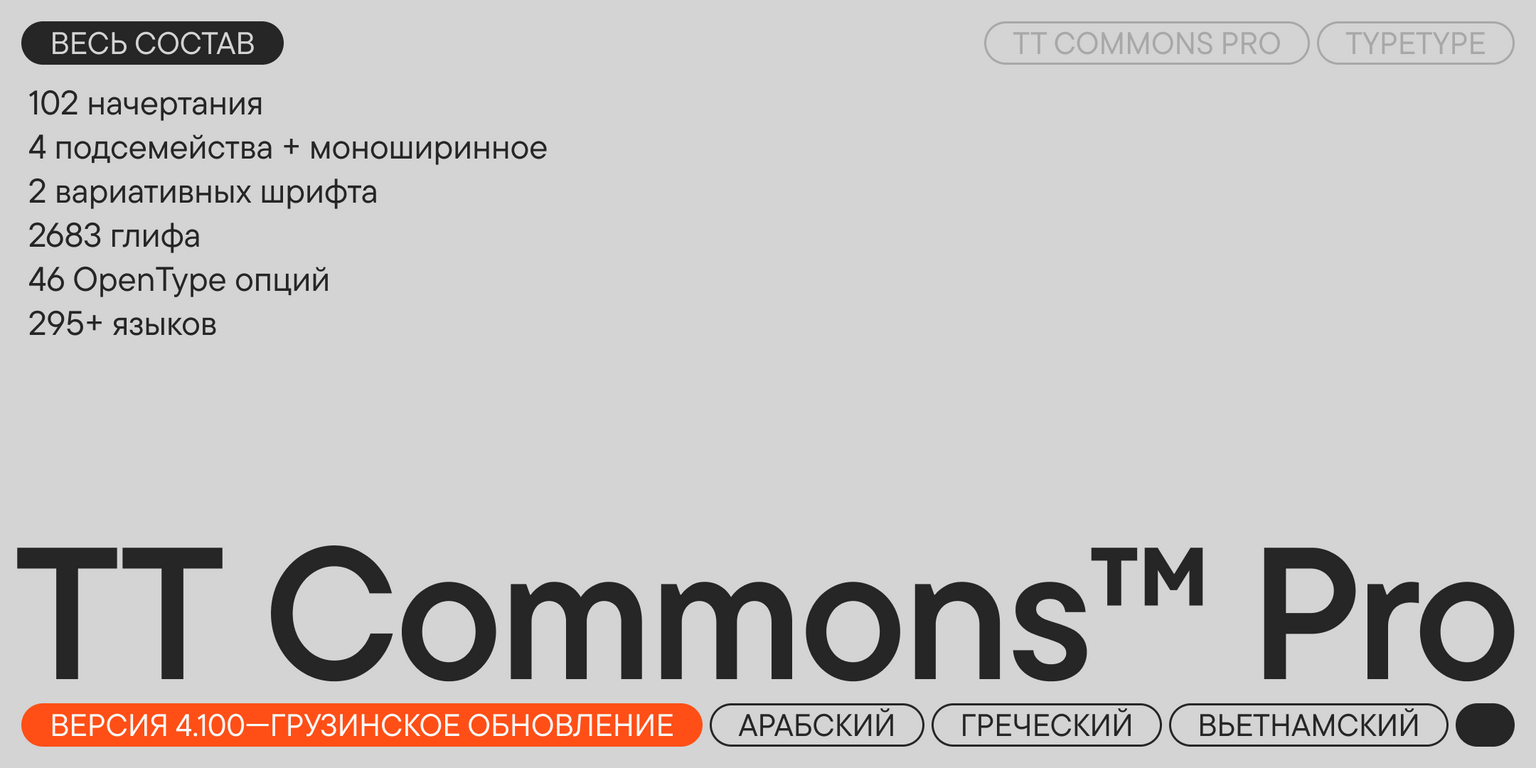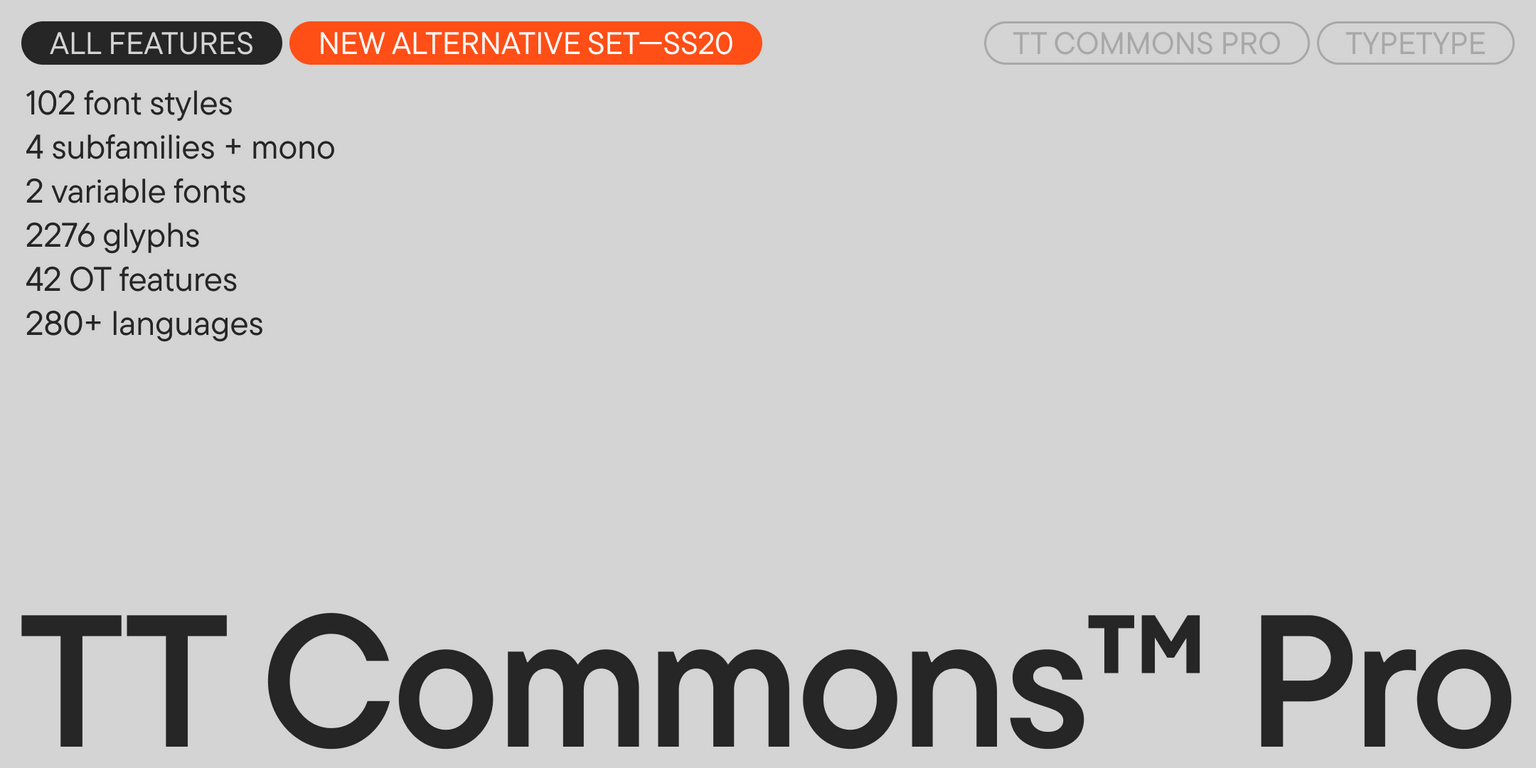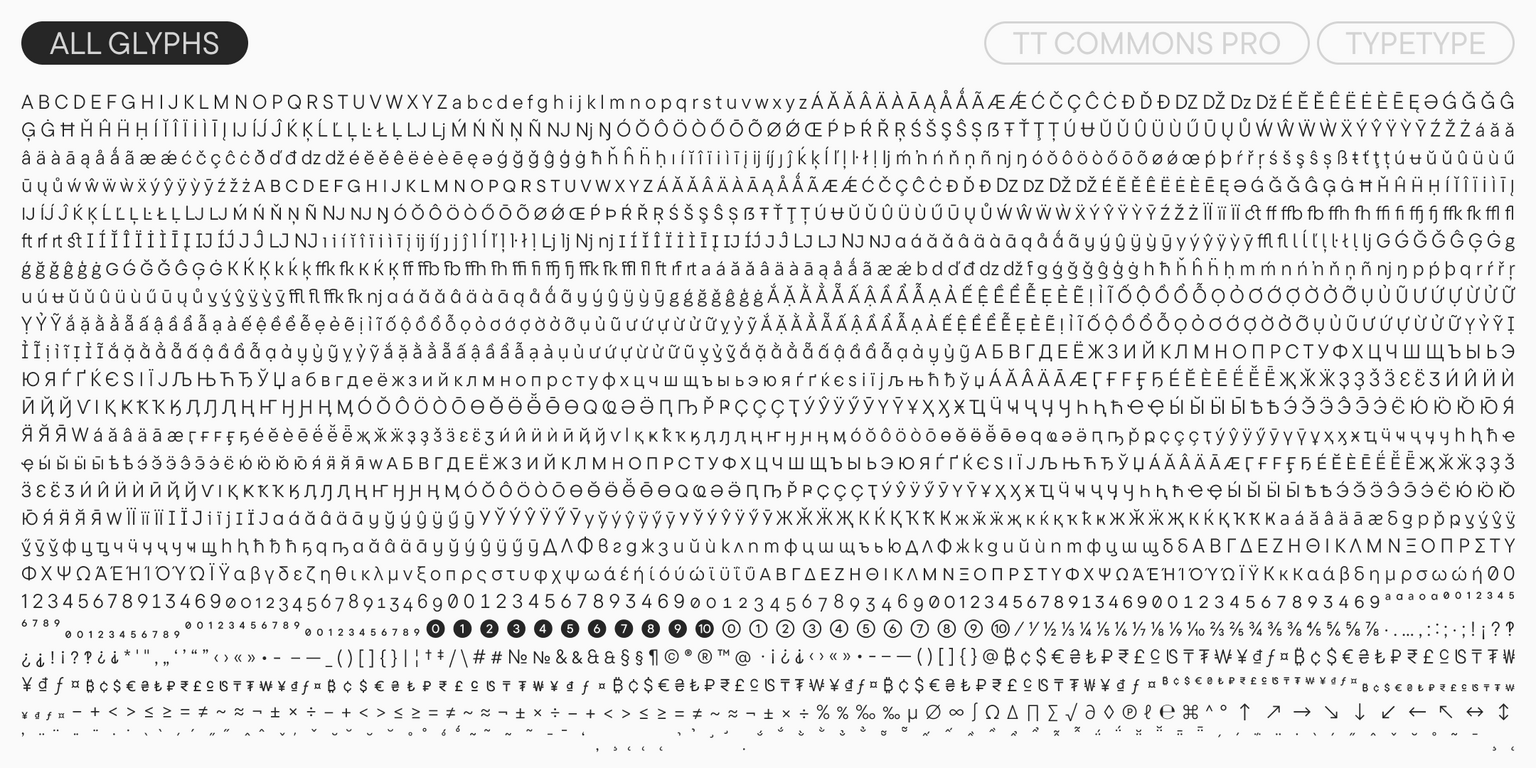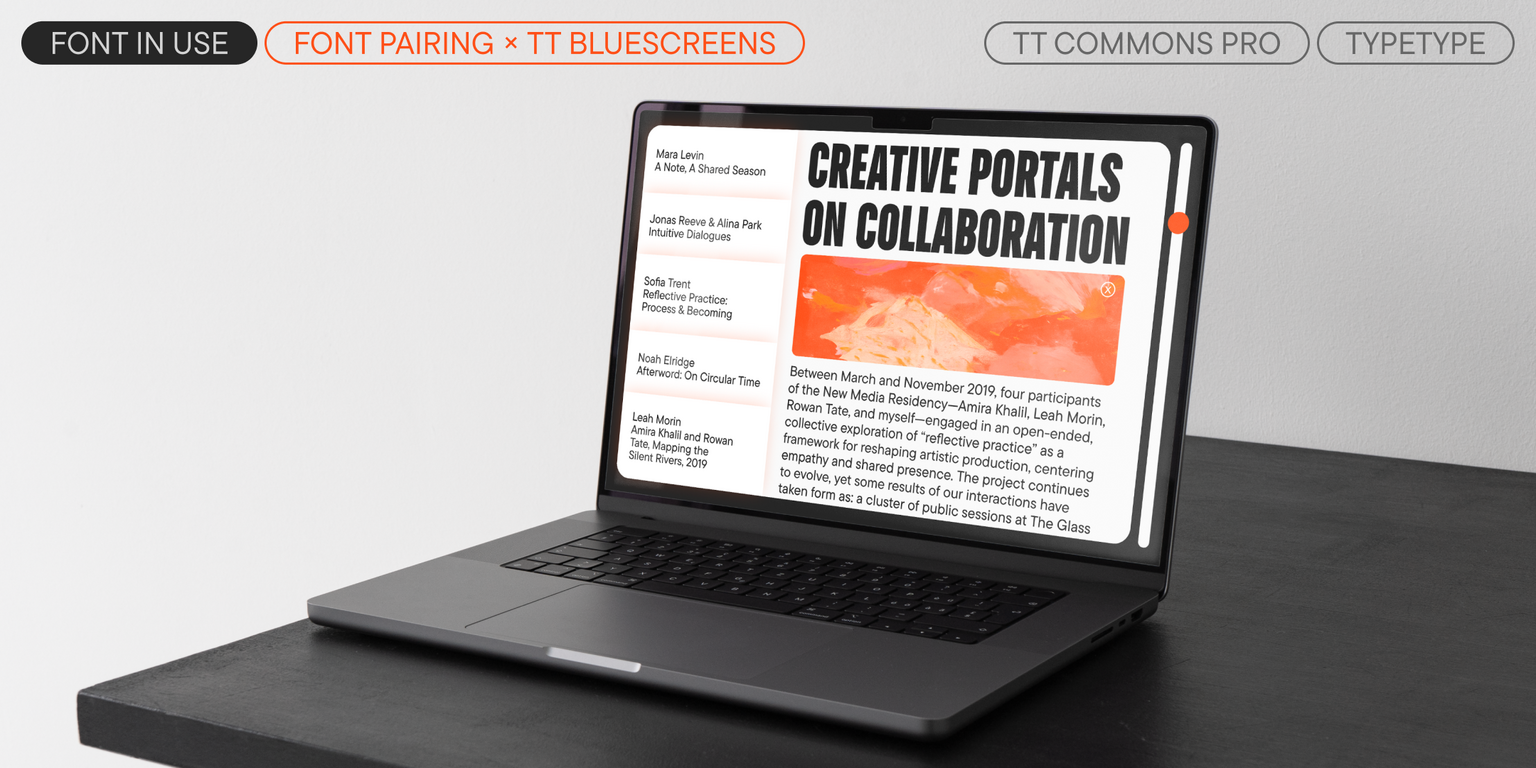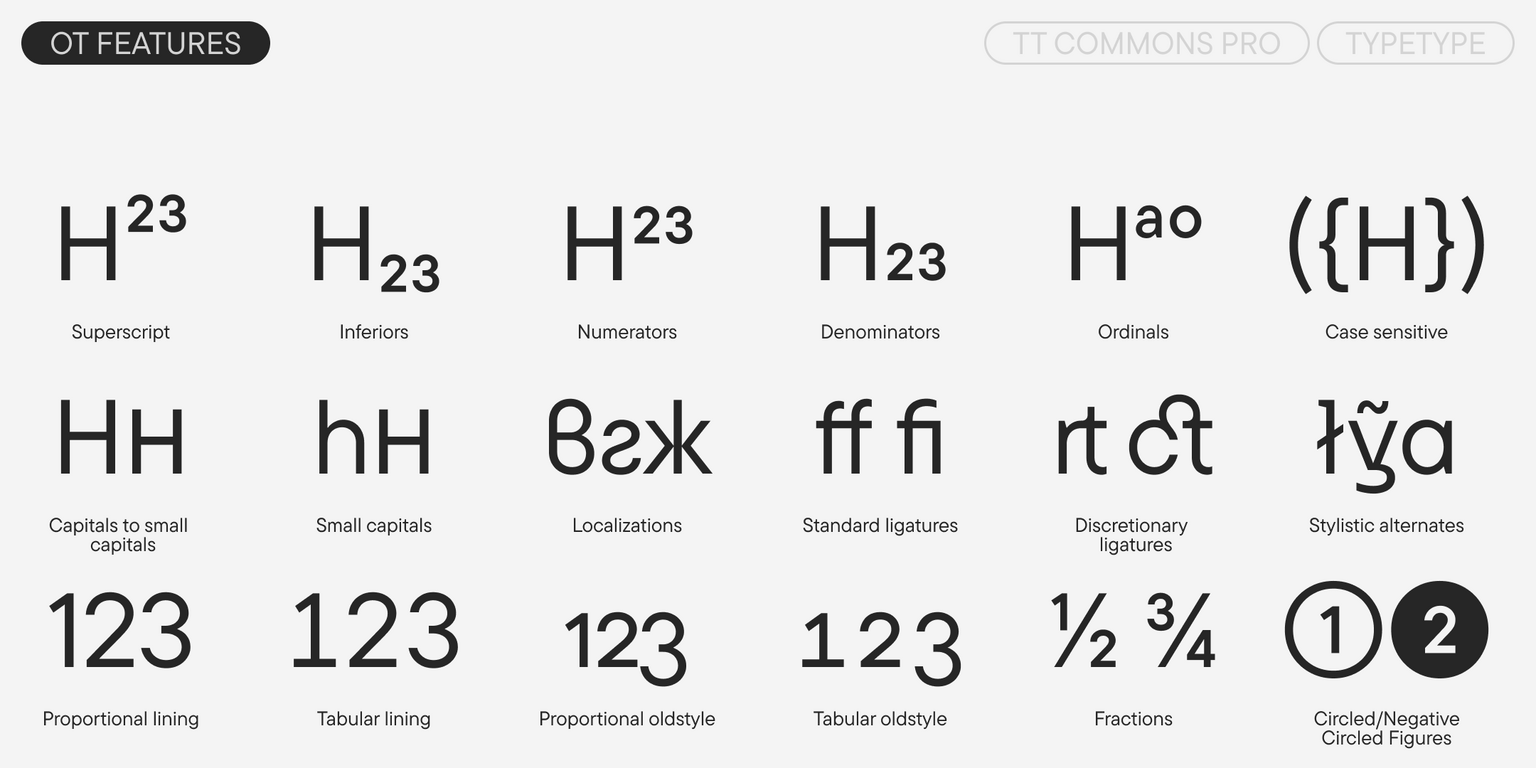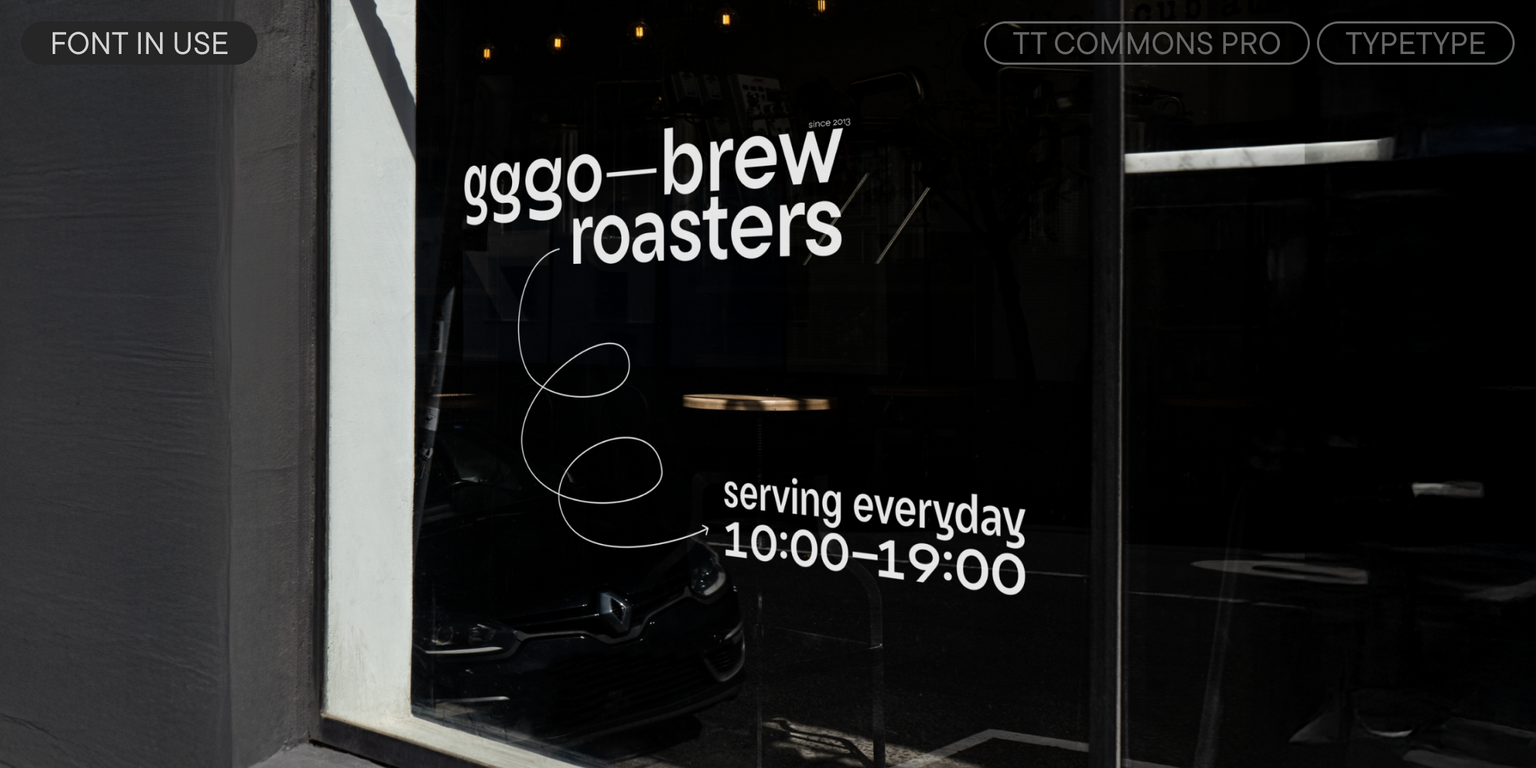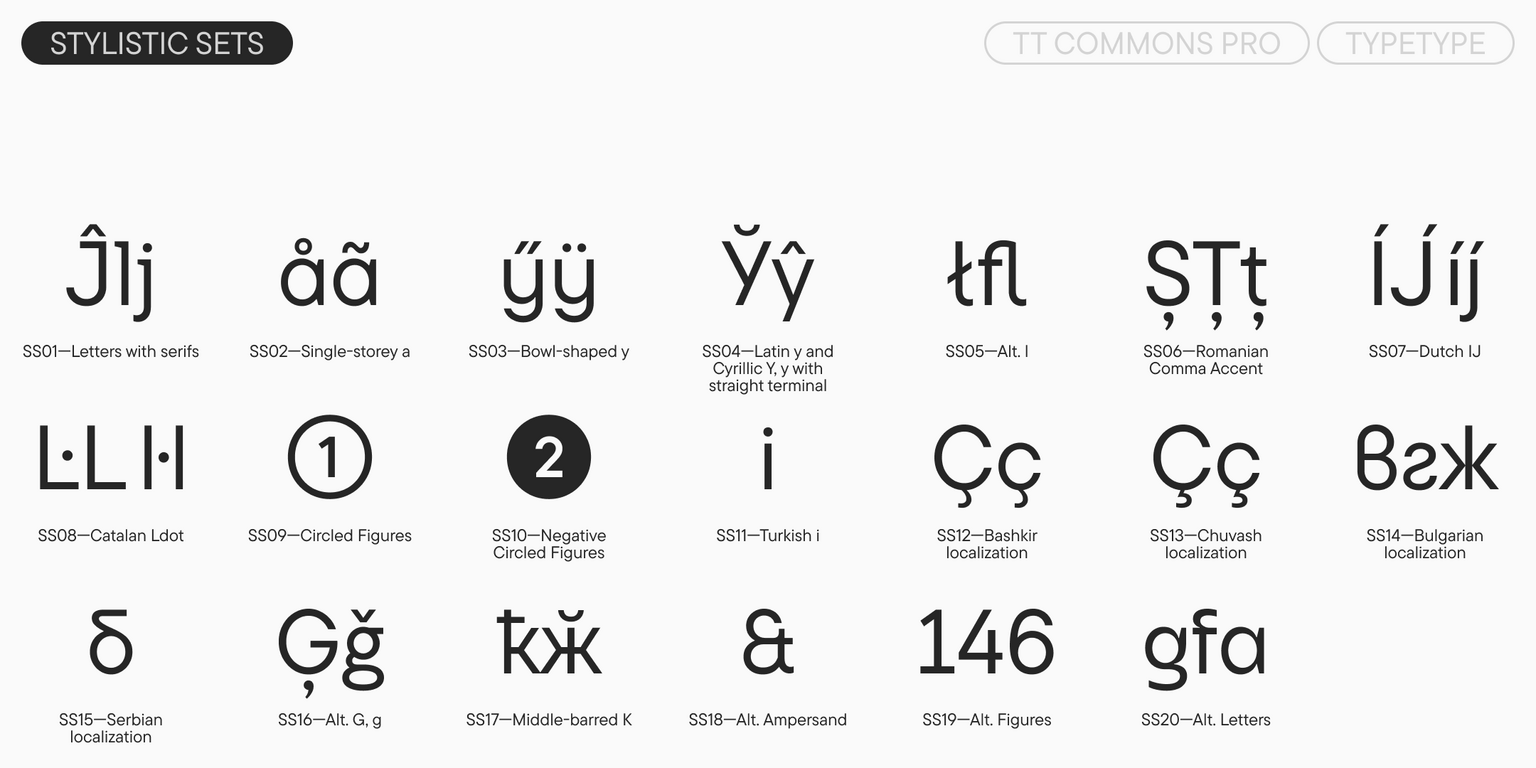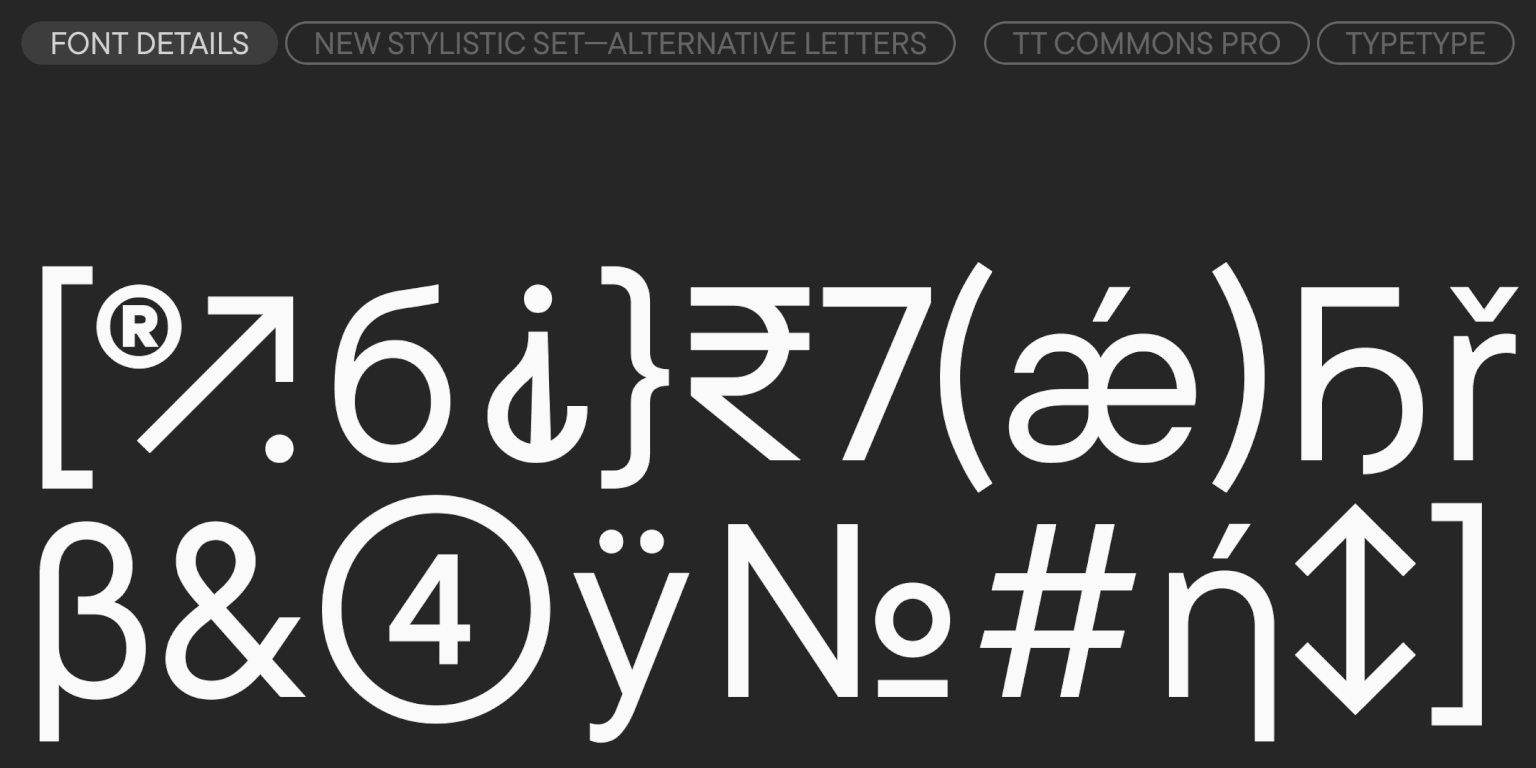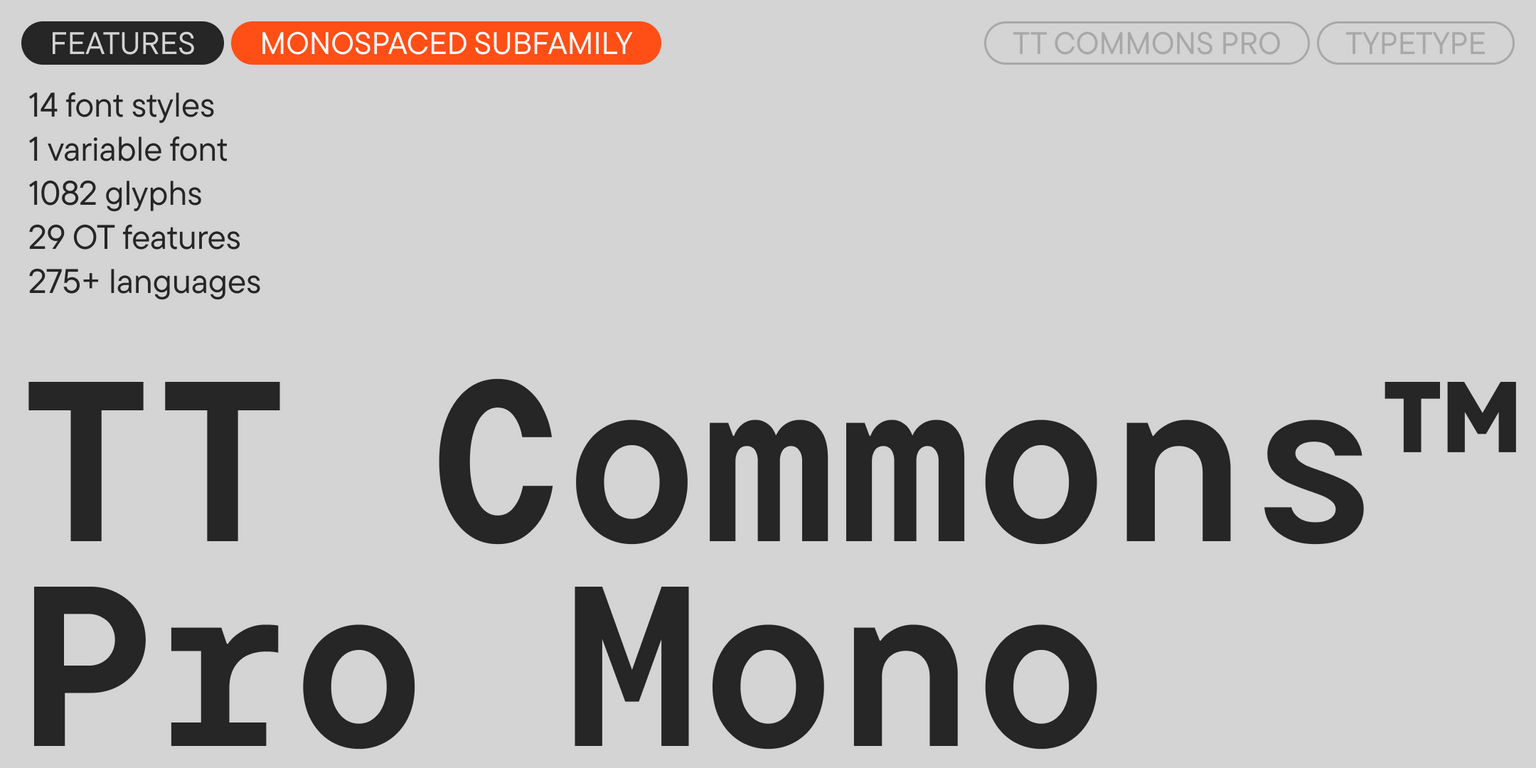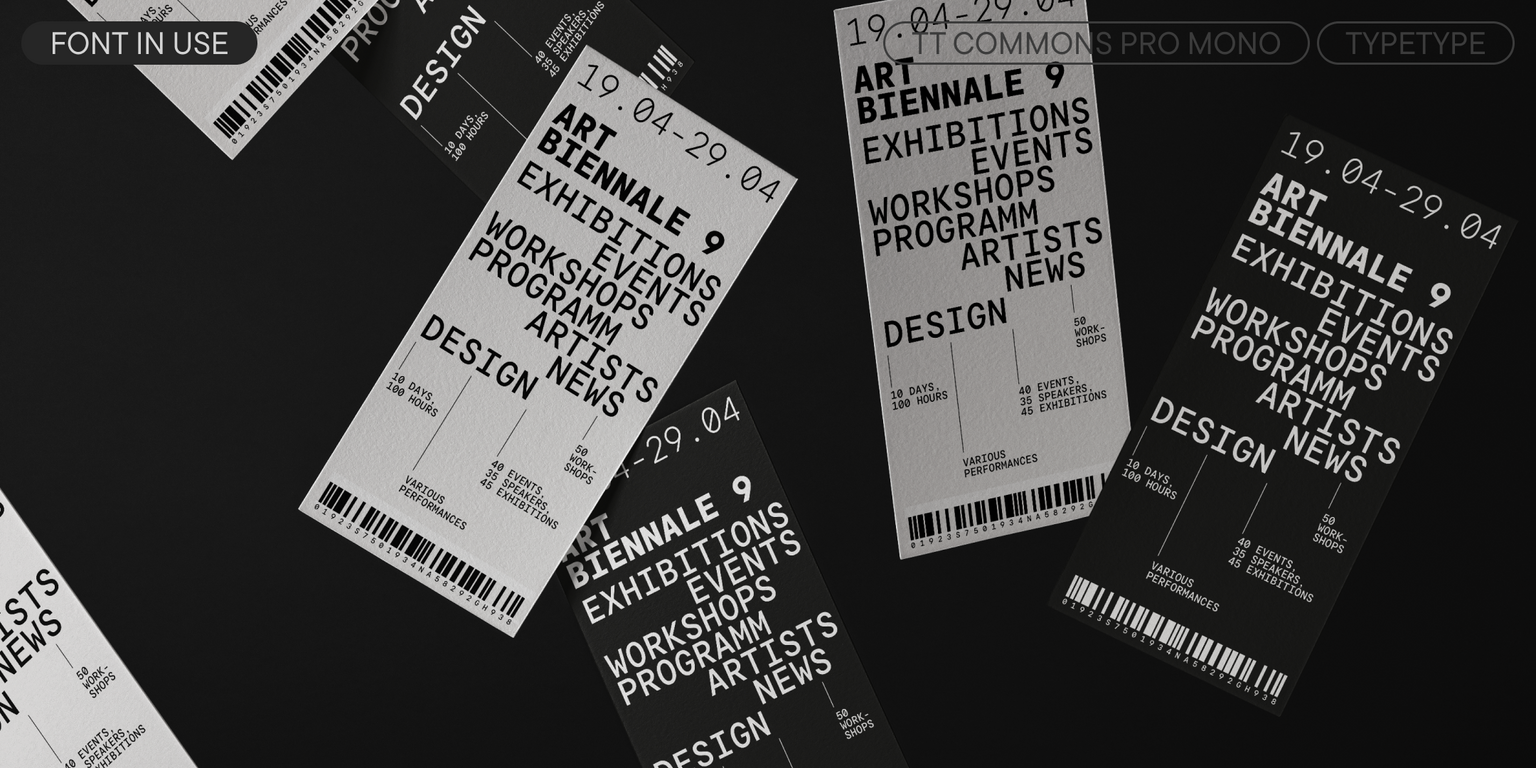
TT Commons™ Pro
TT Commons™ Pro — TT Коммонс Про
TT Commons™ Pro — универсальный геометрический гротеск, один из самых востребованных шрифтов студии. Он подойдёт для любых задач.
TT Commons™ Pro
TT Commons™ Pro — геометрический гротеск, нейтральный и яркий одновременно
TT Commons™ Pro